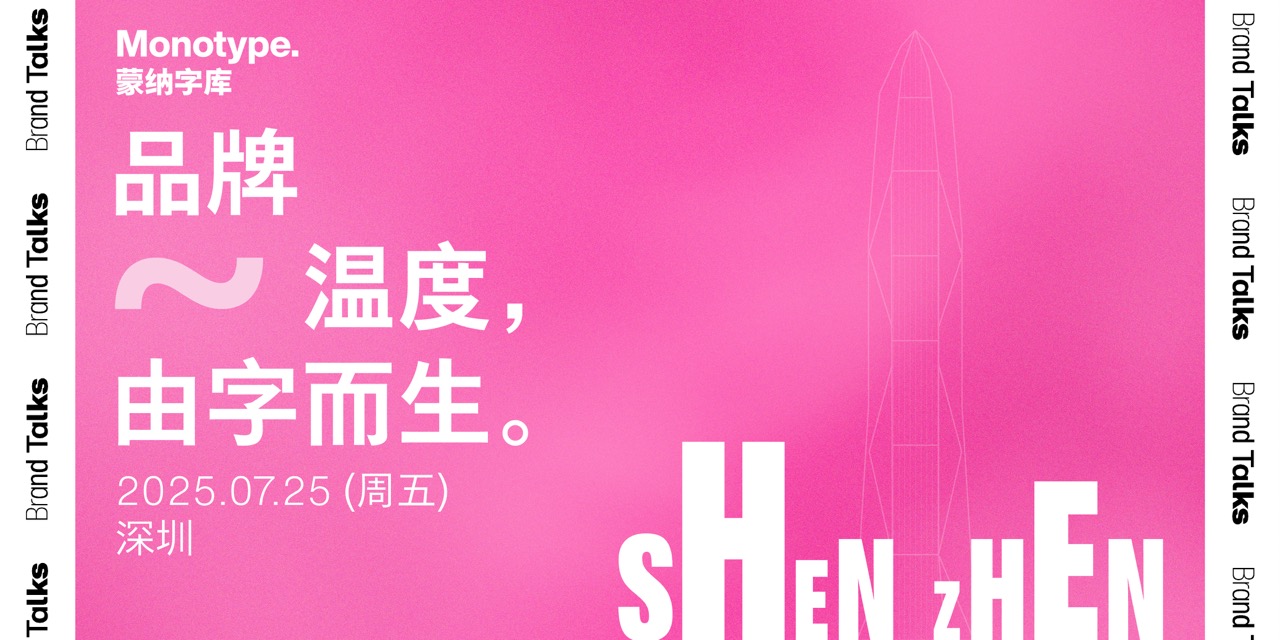
小林章亲临现场!Brand Talks 2025 蒙纳字体与品牌论坛(深圳)报名开启!
夏日正酣时,我们再次来到素有「设计之都」美誉的深圳,于 7 月 25 日(周五)带来「品牌温度,由字而生」蒙纳字体与品牌论坛。
蒙纳传奇字体大师小林章将亲临分享现场,携手蒙纳全球品牌创意总监 Graham Sturt,与三位深耕品牌、字体与视觉语言领域的杰出实践者,通过个人经历与典型案例,呈现他们如何以字体为载体,赋予品牌人文温度,启发更深层的联结与共感。
品牌温度,由字而生。
数字洪流融汇万象、品牌趋光逐影,但人们愈发渴望与饱含温度与人情的品牌真实共鸣。
字体,是视觉起点,是情感媒介。横竖撇捺,藏着语言未能道尽的张力。
品牌温度,不只是口号或图腾,真实镌刻在人们心中的,是透过字体微妙传递出的人情味:或温润包容,或率性豁达,或优雅内敛。
夏日正酣时,我们再次来到素有「设计之都」美誉的深圳,于 7 月 25 日(周五)带来「品牌温度,由字而生」蒙纳字体与品牌论坛。
蒙纳传奇字体大师小林章将亲临分享现场,携手蒙纳全球品牌创意总监 Graham Sturt,与三位深耕品牌、字体与视觉语言领域的杰出实践者,通过个人经历与典型案例,呈现他们如何以字体为载体,赋予品牌人文温度,启发更深层的联结与共感。
小林章
蒙纳字体创意总监
世界知名西文字体设计师,2022 年度 TDC 奖章获得者,在日本被誉为“西文字体第一人”。2002 年,小林章发布了 Optima Nova,即 Hermann Zapf 所设计的 Optima 的现代化版本,并在 2009 年和 Adrian Frutiger 合作,升级了 Frutiger 的同名字体家族。
目前,小林章已经设计了 50 余款字体系列,包括 Avenir Next、Between、DIN Next,还主导了长城汽车、腾讯、阿里巴巴、索尼、瑞银、松下等企业定制字体。此外,小林章还领衔设计了翔鹤、松籁等日文字体。
Graham Sturt
蒙纳全球品牌创意总监
Graham Sturt蒙纳全球品牌创意总监Graham Sturt 拥有超过二十年的国际创意经验,曾在 Interbrand、Superunion 等知名公司担任创意总监职位,服务过包括 WPP、喜力、荷兰国际集团在内的众多全球品牌。
Graham 的作品屡获 D&AD、荷兰创意奖、戛纳国际创意节、欧洲设计奖等国际大奖,是荷兰设计的积极倡导者,亦主持《Dutch Design Heroes》访谈系列,专访荷兰本土最具代表性的设计师。
陈诗祺
阿嬷手作品牌美术指导
阿嬷手作品牌美术指导,前华为 Art Studio 美术指导,先后在欧洲顶奢品牌、国内 top 互联网公司设计部门任职。自由平面设计师、插画师。作品曾入选 apd、Award360° 100 等奖项。
梁 佳
谢谢设计联合创办人与创意总监
谢谢设计联合创办人与创意总监,深圳市平面设计协会会员,南海大地艺术节招牌计划策展人,“字游行”、“街头文字”发起人。
刘 庆
《字谈字畅》制作人兼主播
TheType 编辑
纽约 TDC 顾问理事,国际字体协会(ATypI)会员。字体排印研究者,The Type 编辑、《字谈字畅》制作人兼主播。万维网联盟(W3C)特邀专家,中文排版任务组主席,为国内外各厂商担任字体顾问。
蒙纳字体与品牌论坛
蒙纳公司(Monotype Imaging Inc.)的创立可追溯至 1887 年,一直致力于提供业内高品质产品、技术和服务。目前,蒙纳字库涵盖全球多种语言超 25 万款字体,其中包含多款享誉世界的经典作品,比如:Helvetica,Arial,Times New Roman,DIN 等等。继 Linotype 归入蒙纳后,近年,又有 FontShop Fontsmith,URW,Hoefler&Co,Berthold,Fontworks,Colophon 先后加入蒙纳家族。
蒙纳字体与品牌论坛旨在为各领域的字体爱好者搭建深度分享的平台,为设计师、品牌和营销人员提供实用的知识参考和灵感来源。